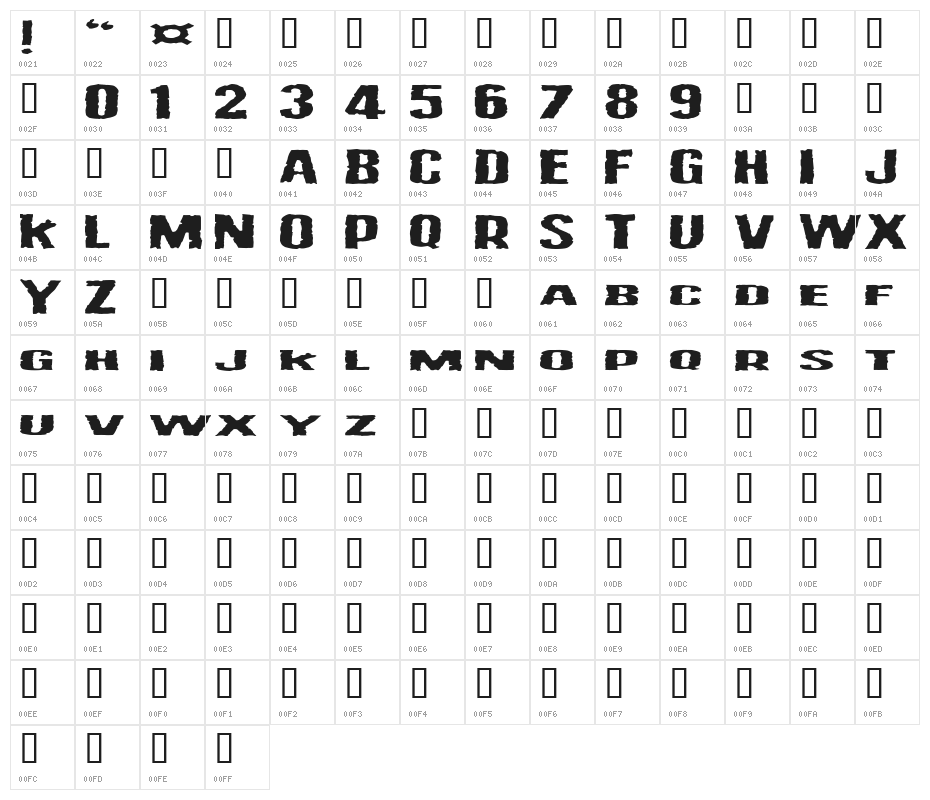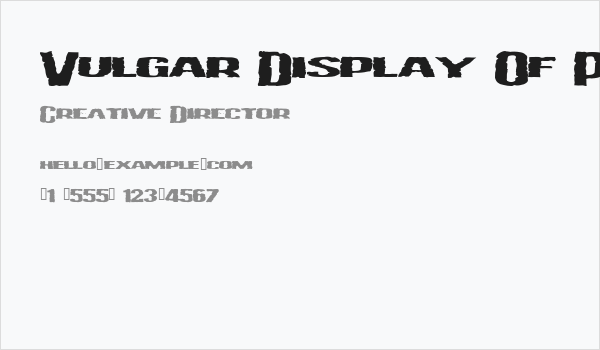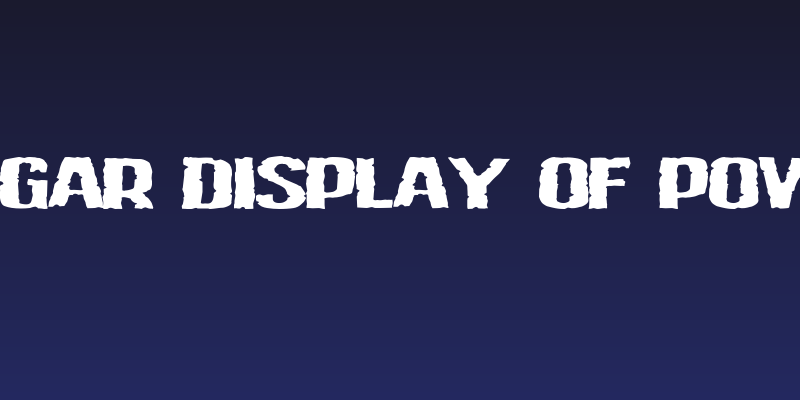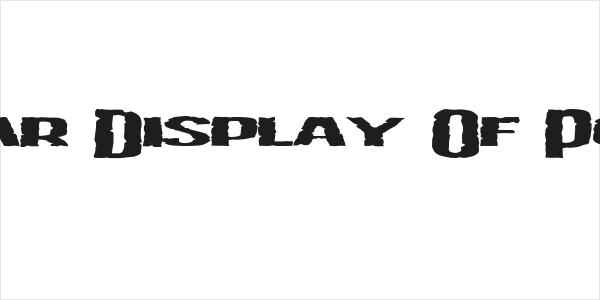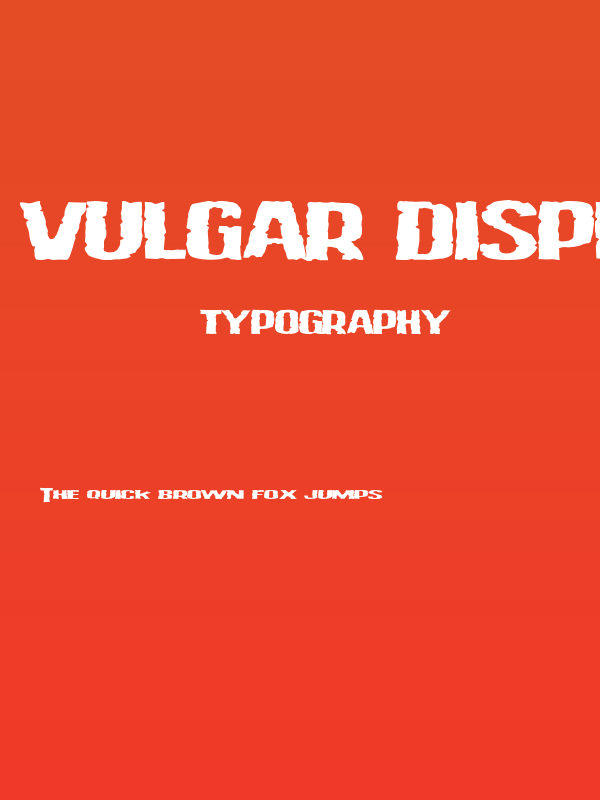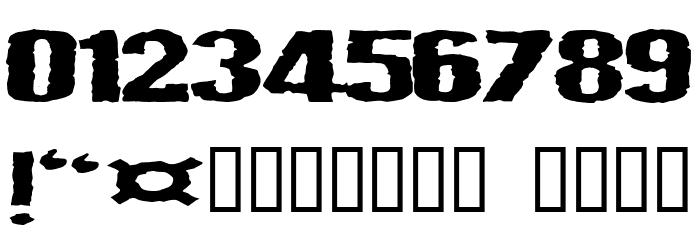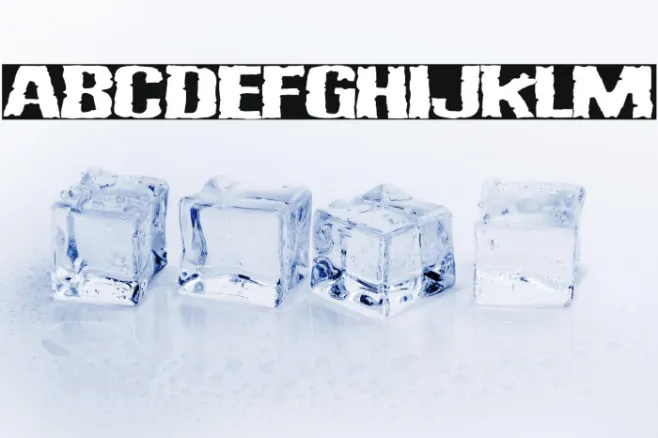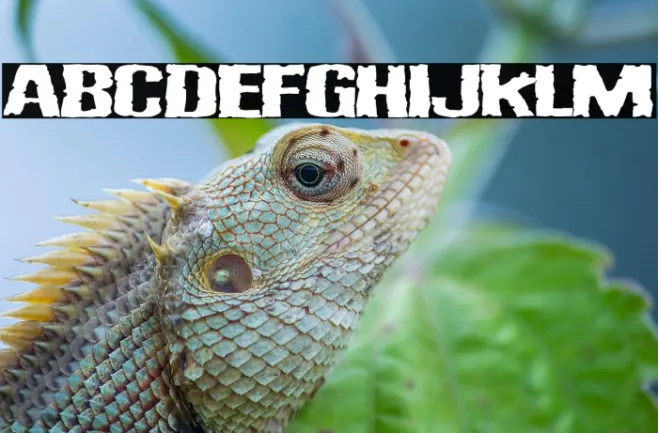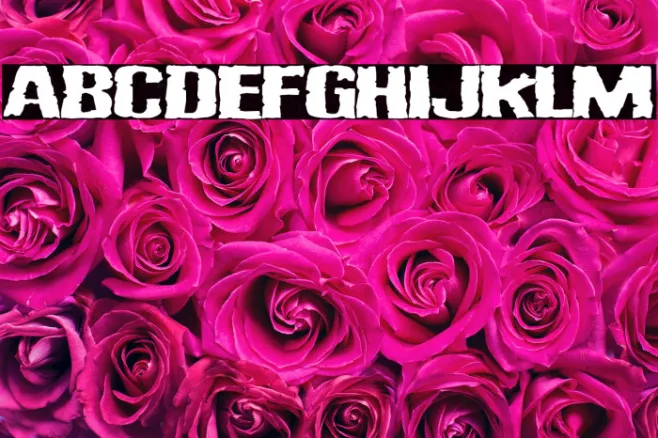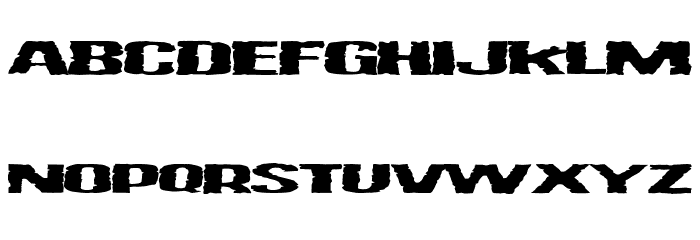
Vulgar Display Of Power Font
| Projets proposés | Album covers, posters, merchandise for rock bands, extreme sports branding, or any project needing a bold, edgy aesthetic. |